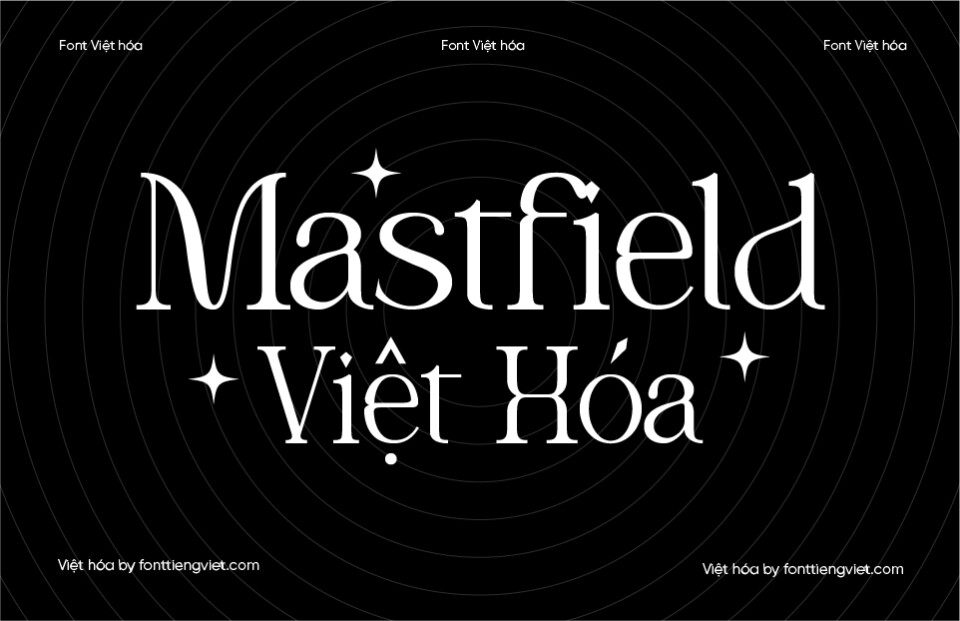
Font Việt hóa 1FTV VIP Mastfield
Trong thế giới sáng tạo, việc lựa chọn một bộ Font Miễn Phí chất lượng luôn là ưu tiên hàng đầu của các nhà thiết kế. Font Việt hóa 1FTV VIP Mastfield nổi lên như một giải pháp hoàn hảo, kết hợp giữa sự hiện đại và nét cổ điển tinh tế. Đây là bộ phông chữ được tinh chỉnh kỹ lưỡng về dấu tiếng Việt, giúp người dùng dễ dàng ứng dụng vào nhiều dự án khác nhau từ học tập đến công việc chuyên môn mà không lo lỗi hiển thị.
Đặc điểm nổi bật của Font Việt hóa 1FTV VIP Mastfield
Bộ Font Việt hóa 1FTV VIP Mastfield thu hút người nhìn bởi những đường nét thanh mảnh nhưng vô cùng chắc chắn. Cấu trúc chữ được thiết kế cân đối, tạo cảm giác chuyên nghiệp và sang trọng cho mọi bản in hoặc hiển thị kỹ thuật số.
Tính ứng dụng cao trong giảng đường và văn phòng
Với các bạn học sinh và giáo viên, việc sử dụng Font Việt hóa 1FTV VIP Mastfield trong các bài thuyết trình hay báo cáo sẽ giúp nội dung trở nên trực quan và bắt mắt hơn. Sự rõ ràng của từng ký tự giúp người đọc không bị mỏi mắt, đồng thời tăng tính thẩm mỹ cho toàn bộ trang văn bản.
Cách sử dụng Font Việt hóa 1FTV VIP Mastfield hiệu quả
Để phát huy tối đa vẻ đẹp của bộ chữ này, bạn nên kết hợp nó với các tông màu trung tính hoặc pastel. Việc điều chỉnh khoảng cách dòng và khoảng cách chữ (kerning) cũng rất quan trọng để tạo ra một bố cục hài hòa nhất. Đây là lựa chọn lý tưởng cho các tiêu đề sách, thiệp mời hoặc logo thương hiệu đòi hỏi sự độc đáo.